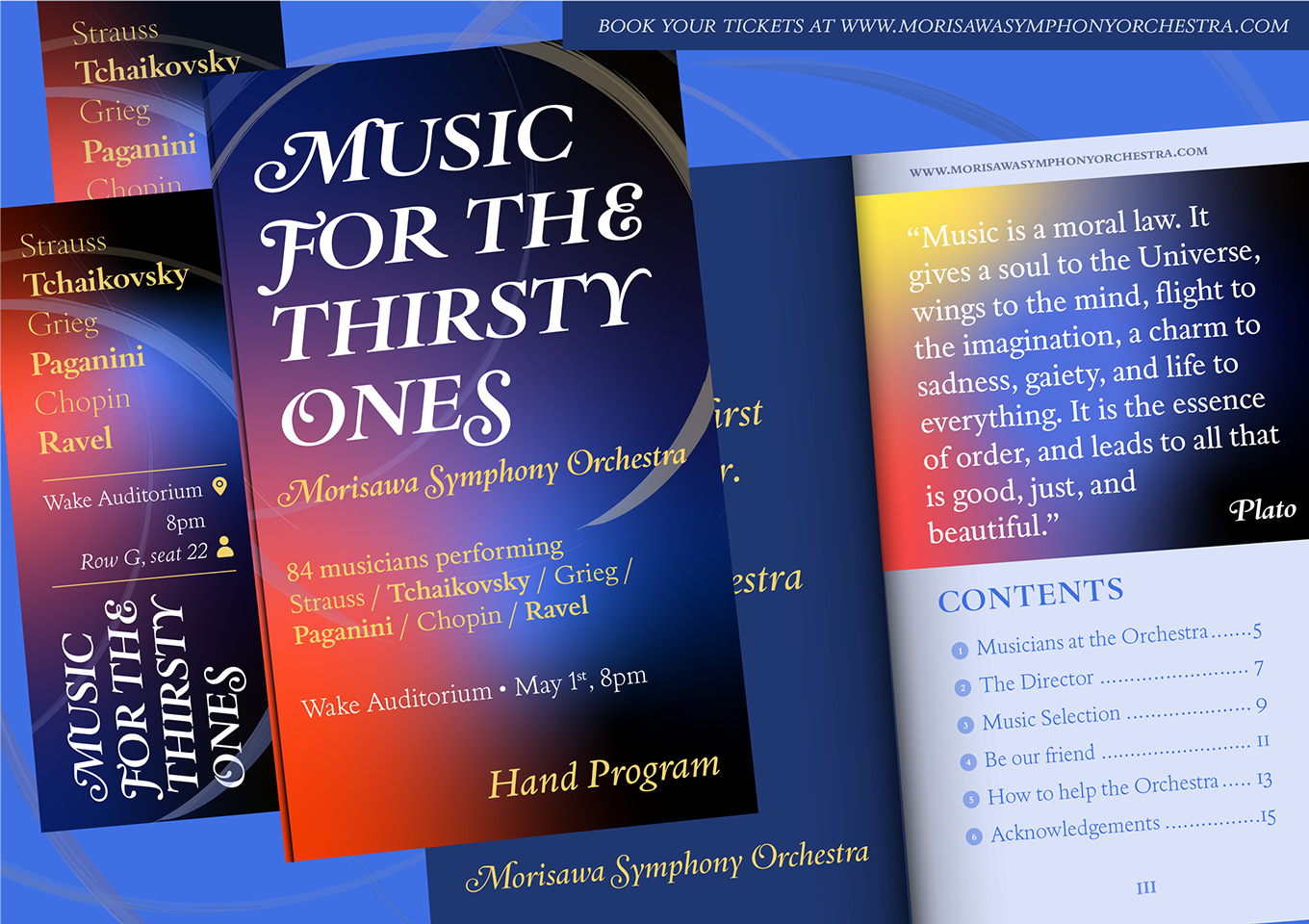
15世紀に印刷されたピエトロ・ベンボの著書で使用された活字にインスパイアされて制作されたオールド・ローマン体です。やや字幅の広い大文字と整備されたアウトラインが特徴で、オールドスタイルでありながら硬質で現代的な表情も持ち合わせます。 サイズ別に最適化された、TextとDisplayの2つのバリエーションが用意され、Displayは見出し利用に最適です。Italicには華やかなスワッシュ字形が搭載されています。